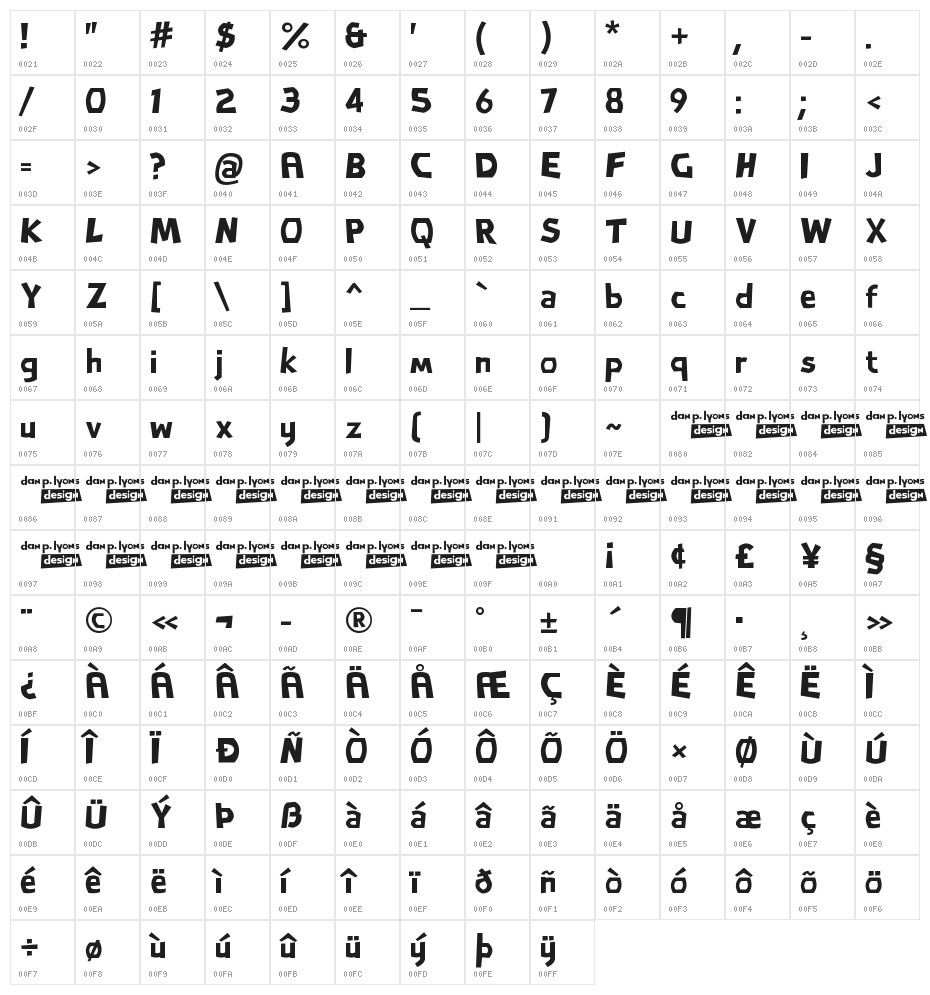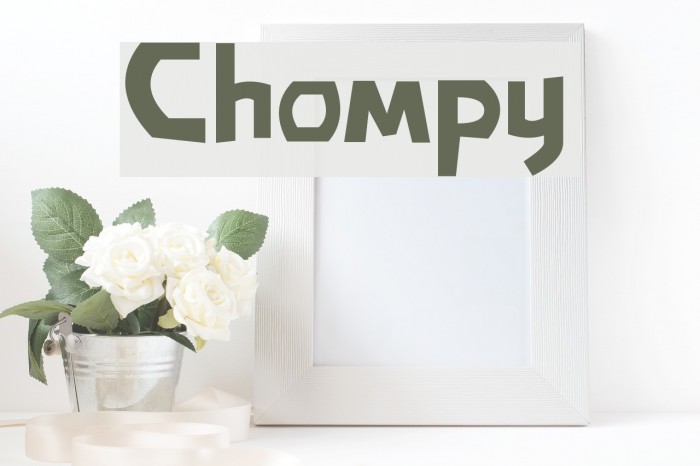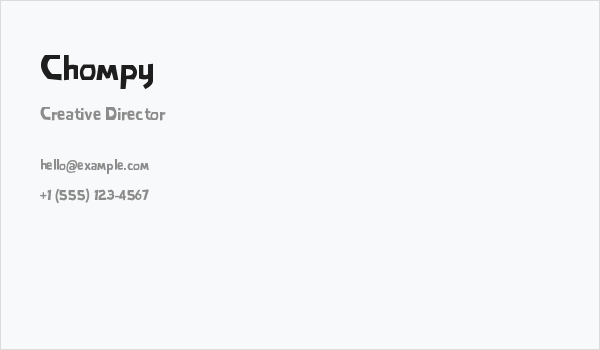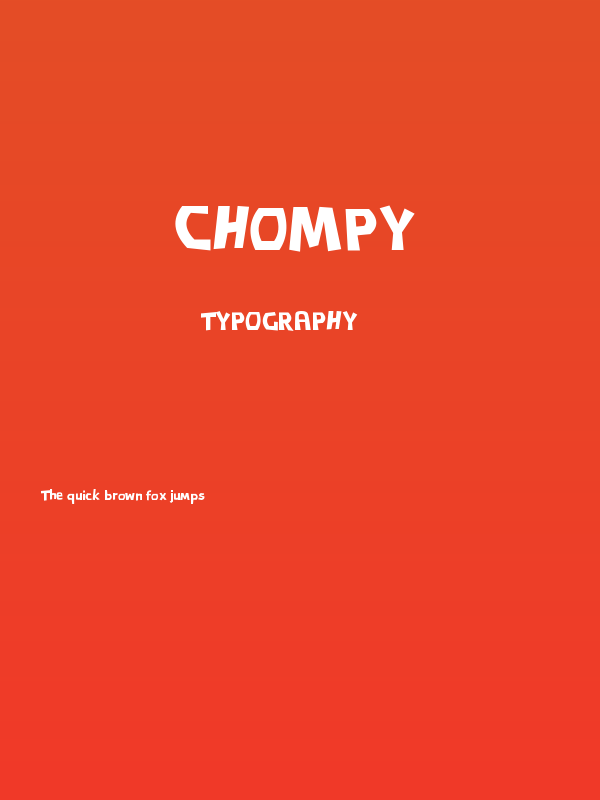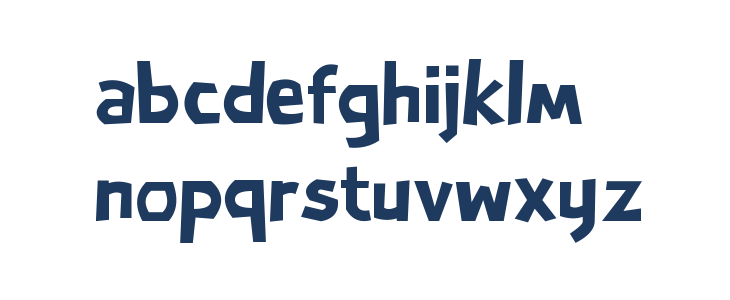
Chompy Font
| Gesamtstil | Playful, Energetic |
| Vorgeschlagene Projekte | Ideal for children's books, comic strips, playful branding, and eye-catching posters. |